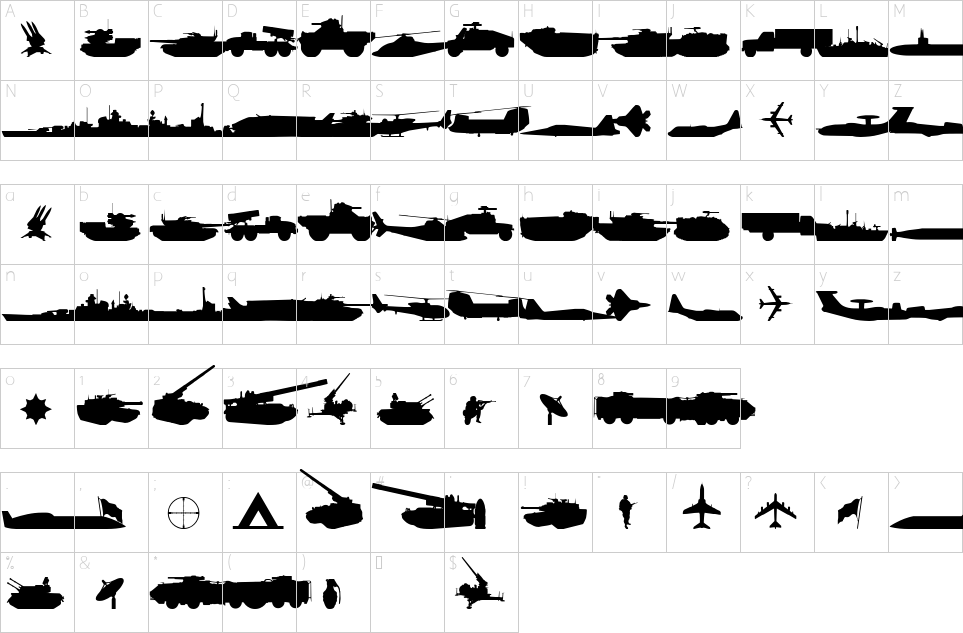
Baixar a fonte ‘Military RPG Font | 1001 Free Fonts’ é uma excelente opção para aqueles que gostam de incorporar um toque de nostalgia militar em seus projetos digitais. Esta fonte foi criada pelo designer Iconian Fonts e é perfeitamente compatível tanto com Windows quanto com Mac. Ela oferece um visual único e moderno, com traços resistentes e detalhes profundos que complementam qualquer estilo de design. Esta fonte foi baixada 7,430 vezes, evidenciando seu valor e diversidade de uso. Se você está buscando adicionar um toque militar ou histórico a seus designs digitais, esta é uma fonte que merece ser considerada.